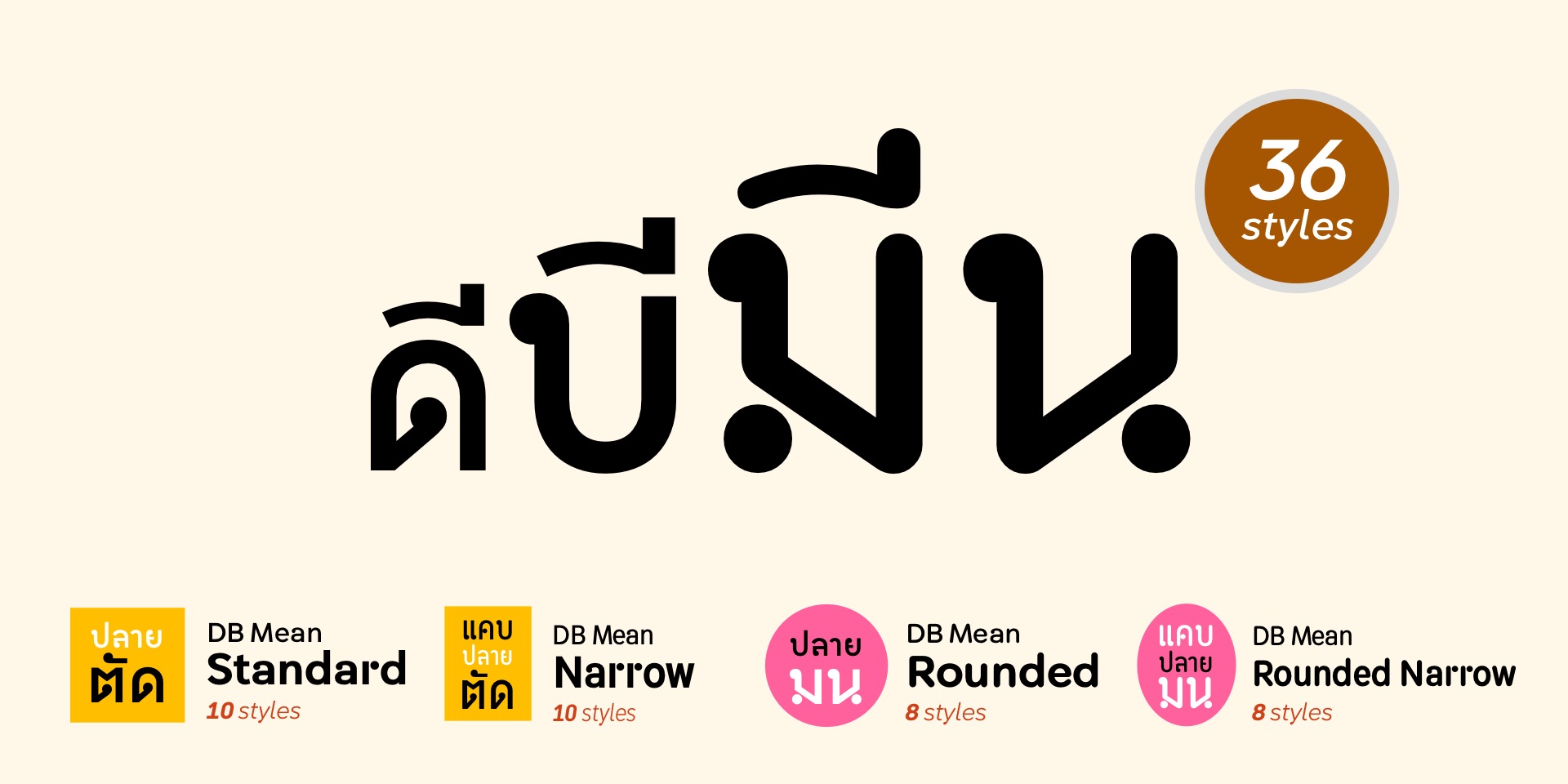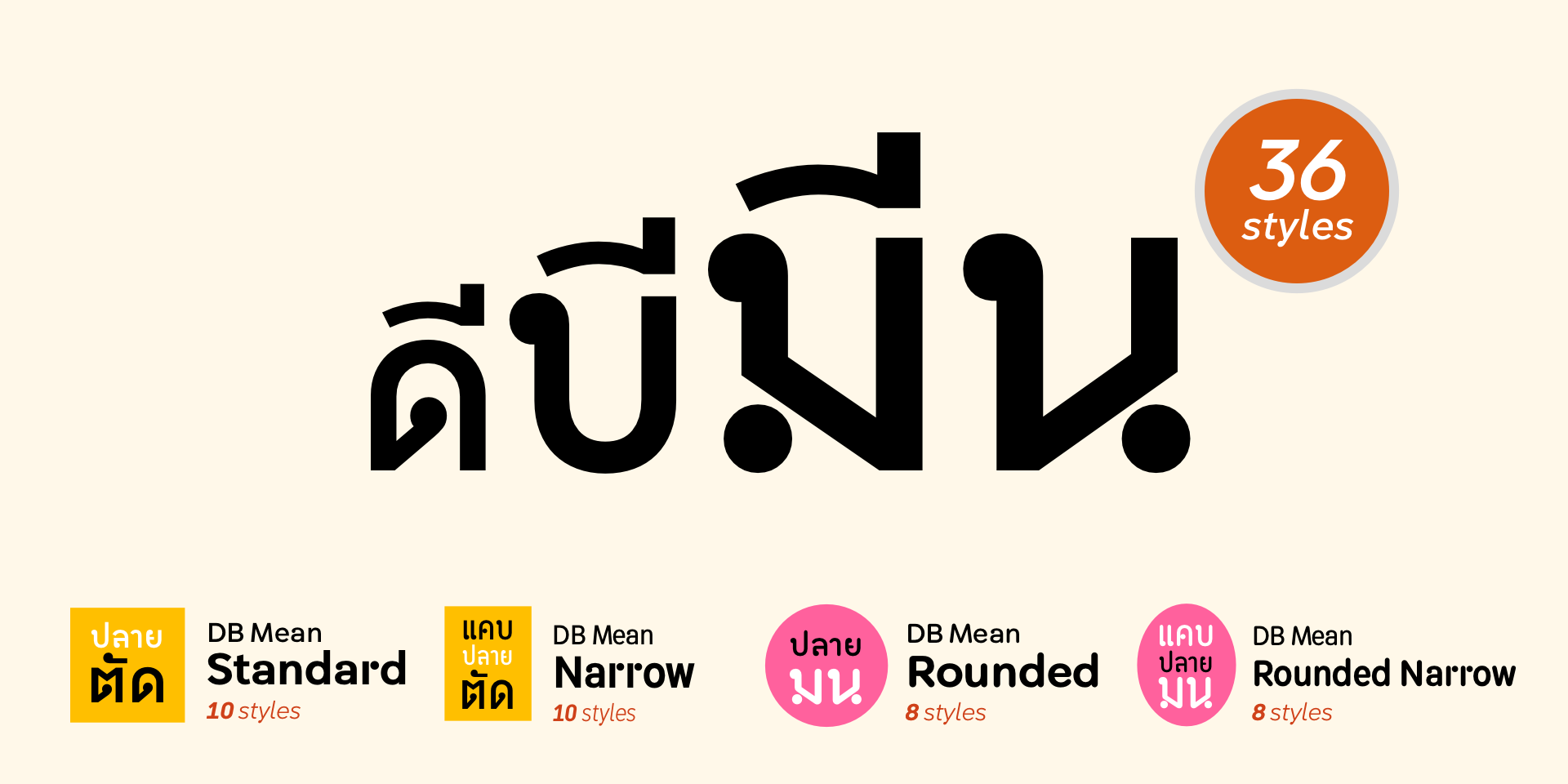
DB Mean Complete Bundle
ดีบี มีน ปลายตัด และ ปลายมน
4 font families,
36 styles
รวมชุด ฟอนต์
DB Mean และ DB Mean Rounded
ปลายตัดและปลายมน
ตัวกว้างปกติและตัวแคบ
ที่เป็นตัวพาดหัวก็ได้ เป็นตัวพื้นก็ดี
4 font families
ดีบี มีน
10
styles
ดีบี มีน แนโรว์
10
styles
ดีบี มีน ราวนด์
8
styles
ดีดี มีน ราวนด์ แนโรว์
8
styles